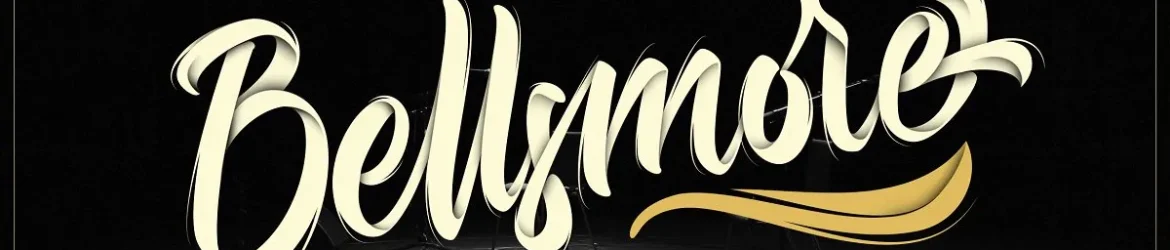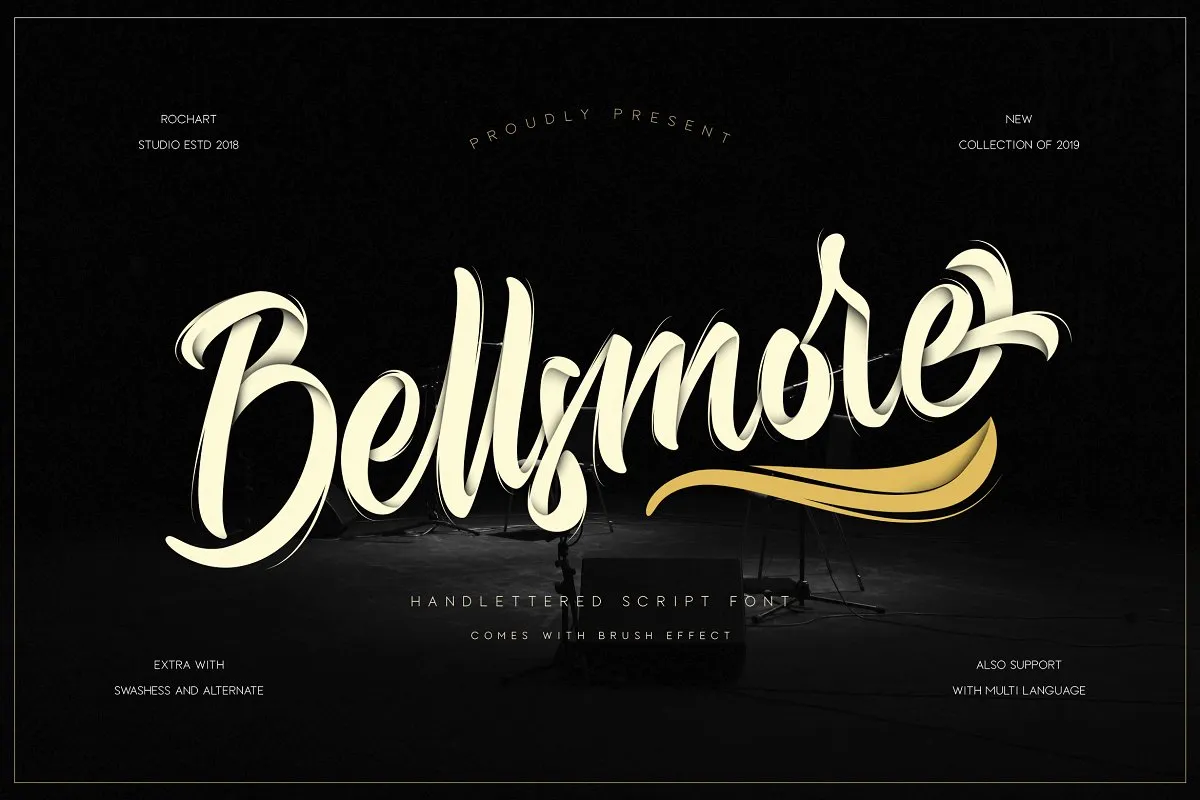
Bellsmore Brush Font – Fonte Grátis
Bellsmore Brush Font
A fonte Bellsmore Brush é perfeita para quem procura uma mistura suave e elegante. Desenhada com a ponta de um pincel, essa fonte se destaca como opção ideal para criações manuscritas artísticas, seja usada no estilo tradicional ou como base para trabalhos mais modernos em tinta ou água-claro. Com sua variedade de alternativas e alguns desenhos curvados, Bellsmore oferece uma fonte que se complementa perfeitamente. Perfeito para design de logomarca, camisetas, anúncios, embalagens, convites de casamento e muito mais, o estilo Brush Script da fonte Bellsmore é um recurso indispensável no arsenal de qualquer designer gráfico.